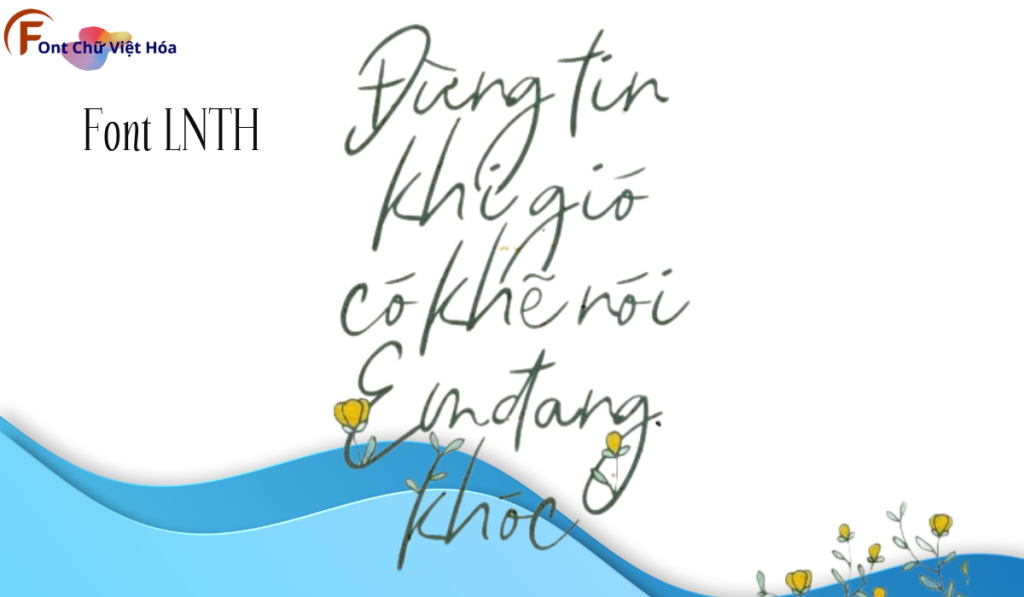
Font LNTH Asmudila Việt Hóa
Font LNTH Asmudila Việt Hóa là một font chữ mềm mại, thuộc bộ LNTH, với thiết kế tròn trịa và thân thiện. Phong cách của font này phù hợp với các dự án thiết kế cần sự ấm áp và dịu dàng, như thiệp mời, bìa sách, hoặc logo. Font LNTH Asmudila Việt Hóa mang đến sự mềm mại và dễ nhận diện, ứng dụng trong các lĩnh vực sáng tạo. Đặc điểm hình dạng của font bao gồm các đường nét mềm mại và tròn trịa, giúp tăng tính thẩm mỹ và sự chú ý. Việc Việt hóa font giúp người dùng dễ dàng sử dụng trong các thiết kế tiếng Việt, mang lại sự tiện lợi và linh hoạt.